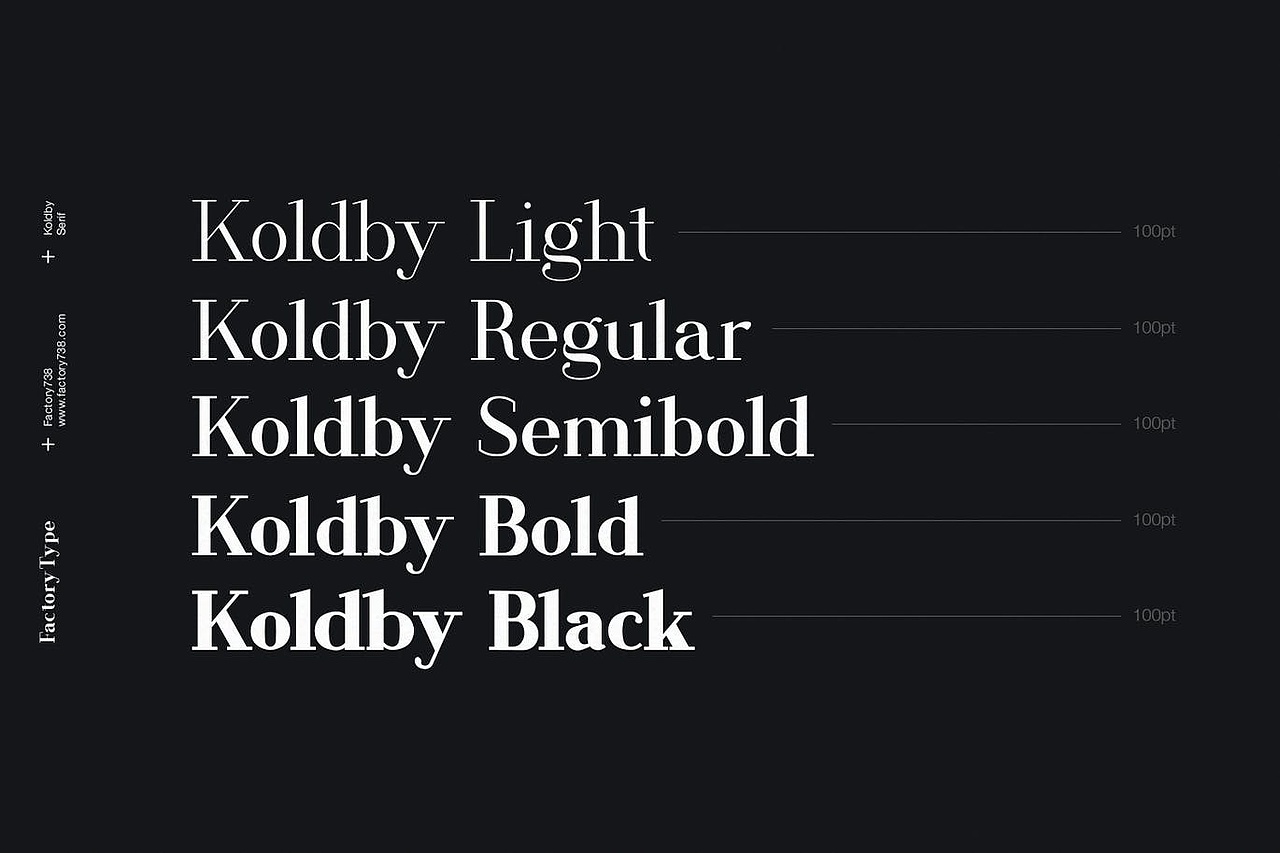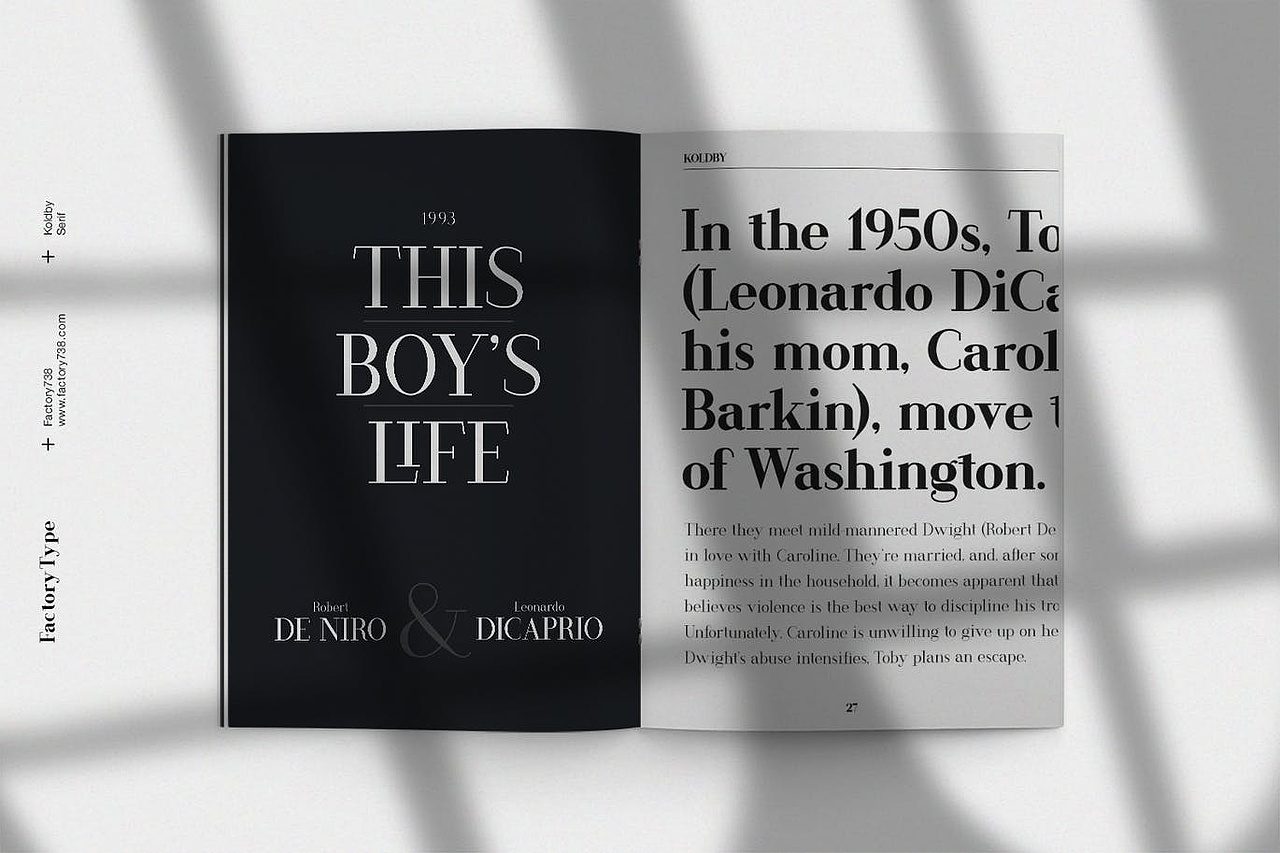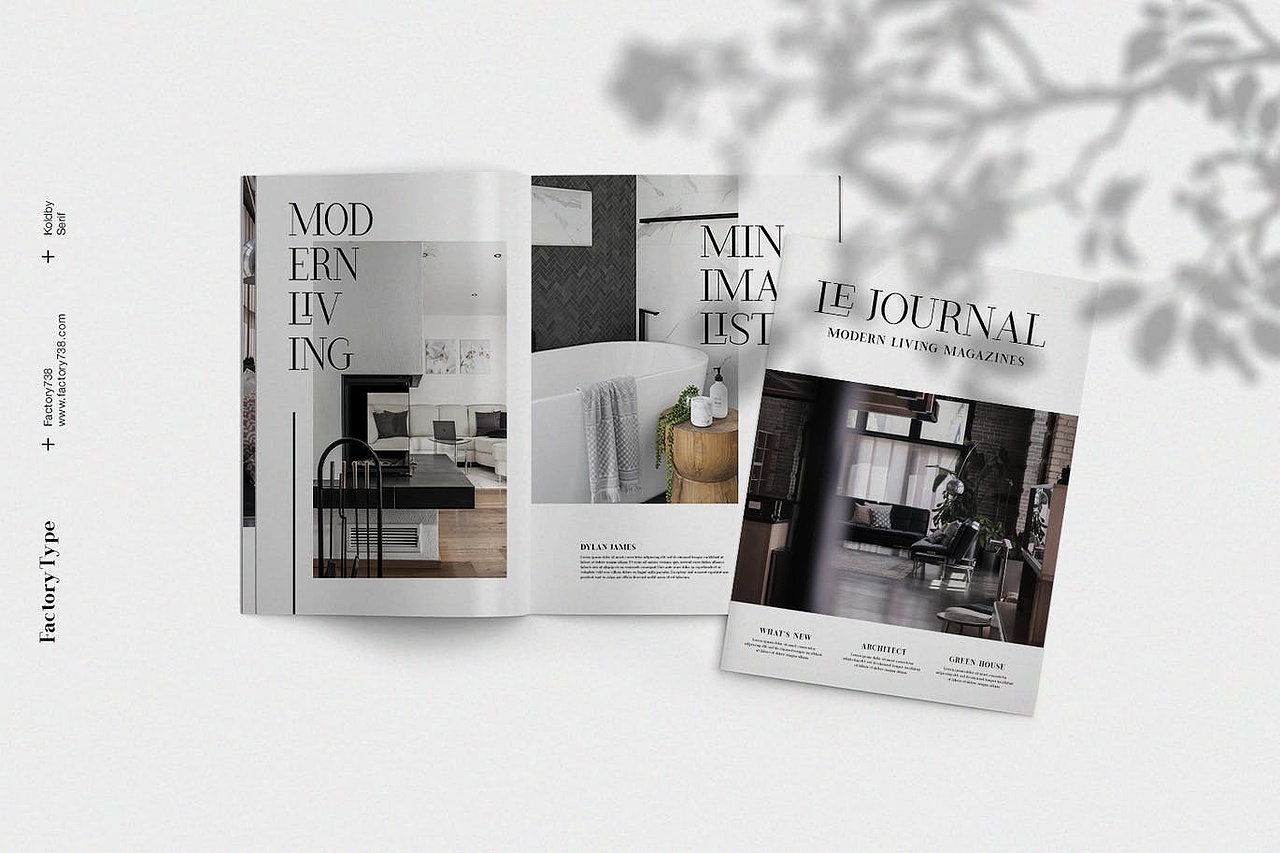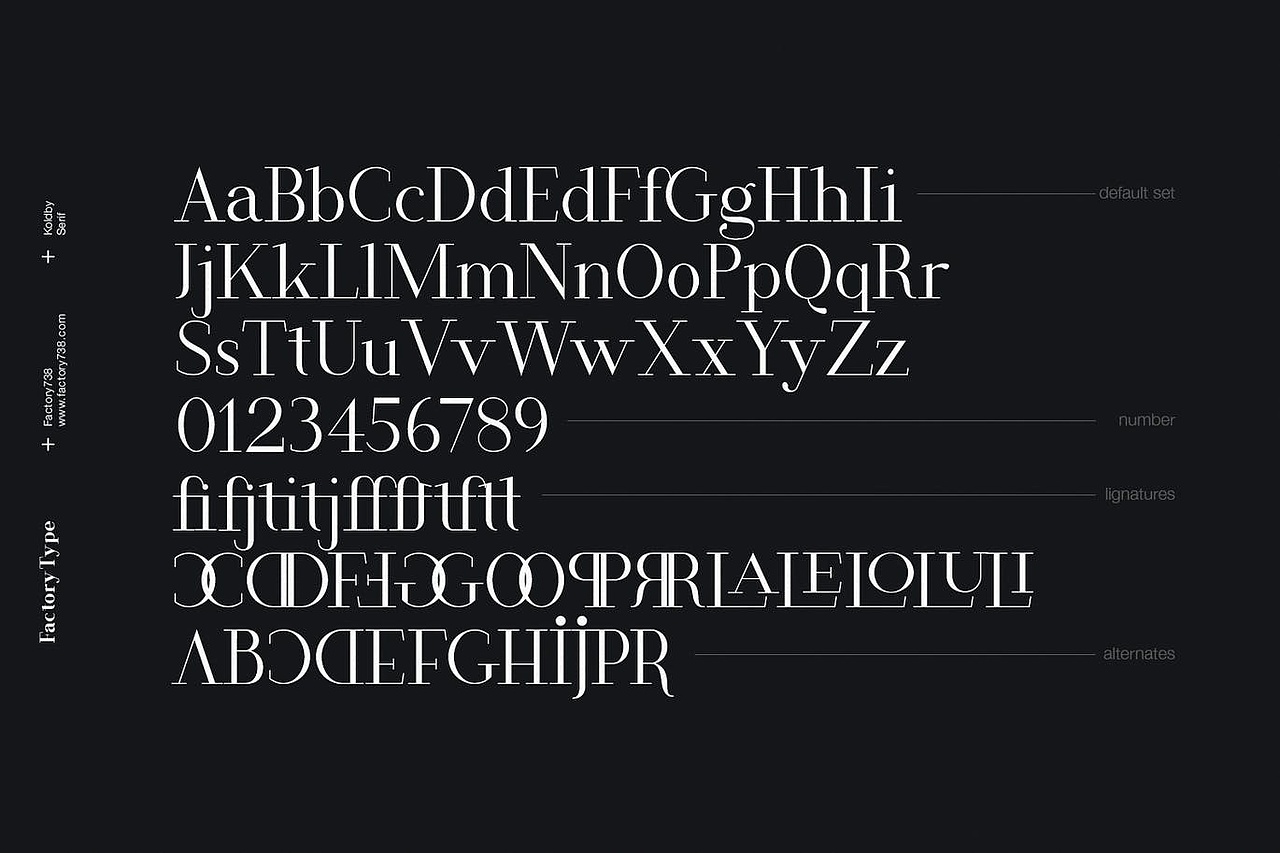
koldby字体设计
Koldby是一个现代而优雅的衬线字体家族。现代和复古元素的结合赋予了优雅的设计。各种权重提供了多种选择,可以帮助您找到适合您项目的最佳印刷颜色。较轻的重量非常适合于正文,而较重的重量则非常适合具有高影响力的头条新闻。可用的样式Ligature和Alternate提供许多不同的字符,使您的项目设计或徽标具有独特的外观。